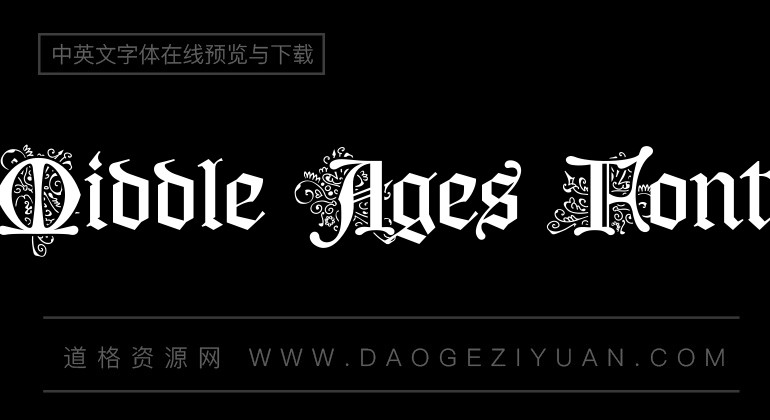
Middle Ages Font
Middle Ages Font是一种仿古代手写风格的字体,通常用于与中世纪相关的设计和文本排版。它的字母形状和线条充满了中世纪手稿的感觉,让人联想到古老的手写书籍和文献。 此字体的特点是具有很强的装饰性和艺术性,每个字母都很精致,有许多花纹和细节,其中一些字母还具有饰物和附加符号。这种字体的使用通常会为设计增添一份神秘感和历史感,适用于创作中世纪风格的海报、标志、书籍和其他设计项目。 总的来说,Middle Ages Font是一种独特的字体,适用于需要中世纪风格的设计和排版,给人以古老、神秘和文化的印象。
Middle Ages Font是一款非常不错的手写艺术字体,具有很好的视觉感,适合于文化类的宣传设计、商业类品牌的广告和产品包装设计以及个性化文字排版等较多场景。